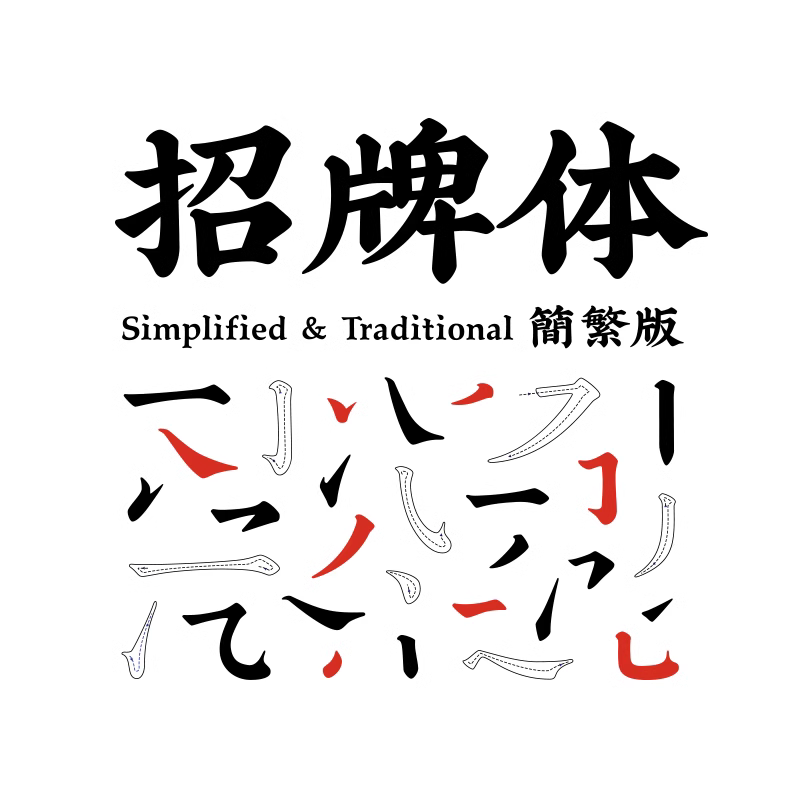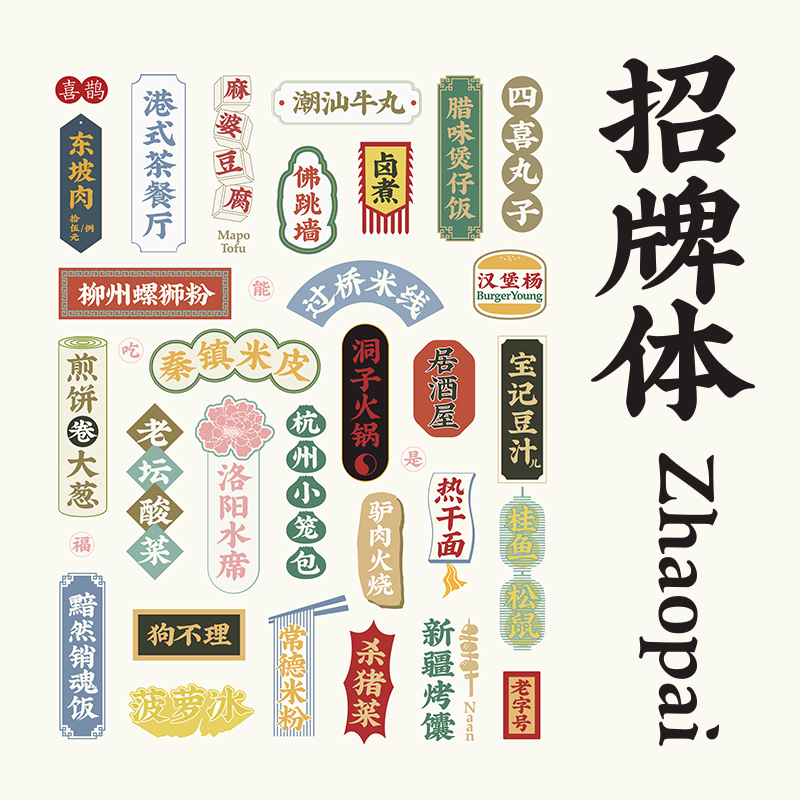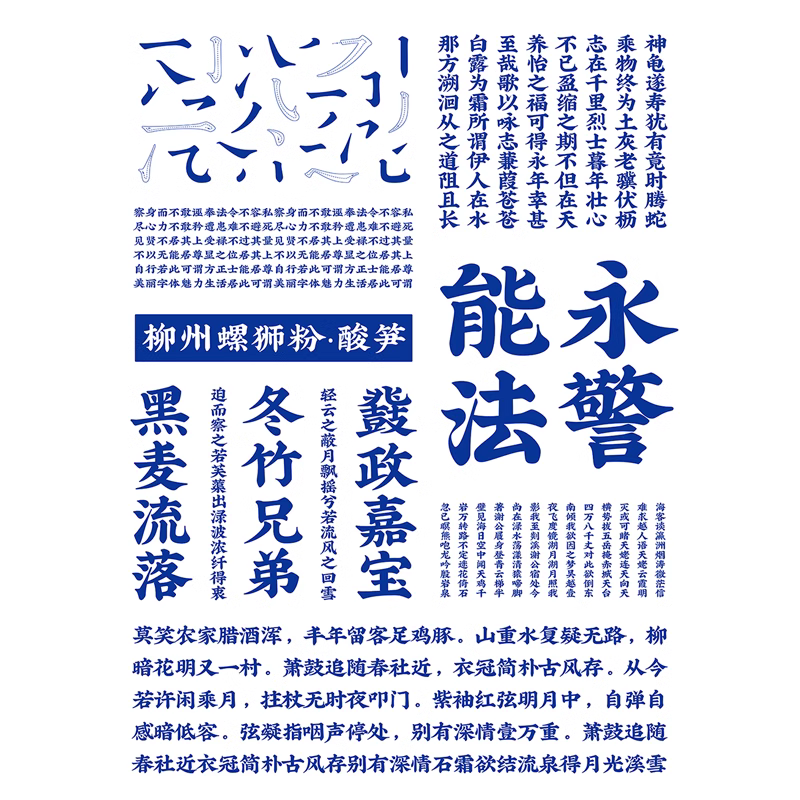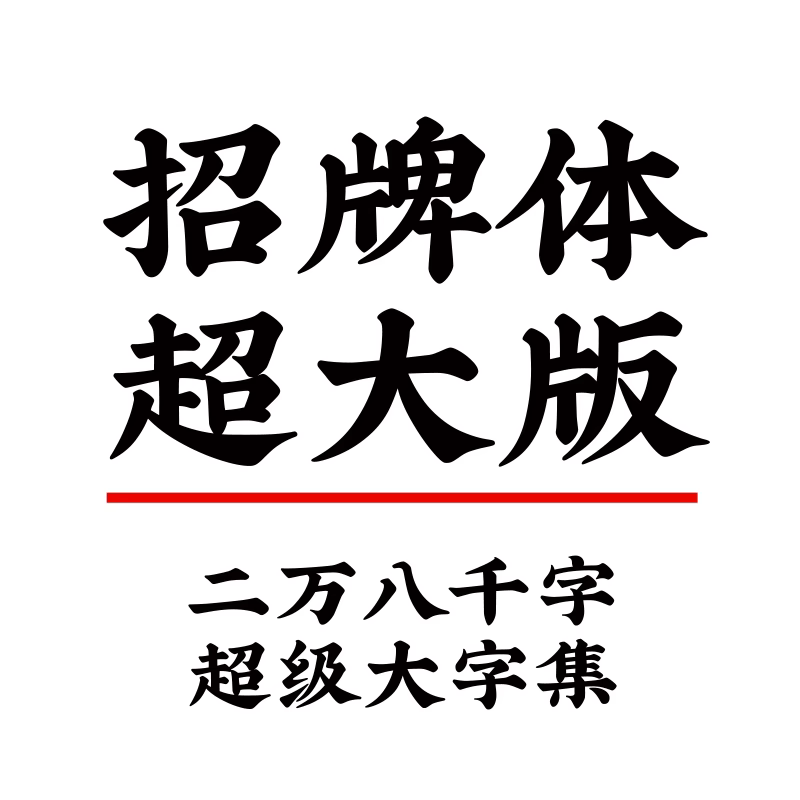
【喜鹊招牌体】字体介绍:
参照嘉靖时期古籍魁本大字本五经古字而创作,设计上追求一种朴实、诚恳、有亲近感有气质的书法风格现代字体。
适用风格:适用于中式味道偏复古的标志标题等文字需求,如餐饮、文创品牌、中式食品、影视字幕等。
2017 Granshan非拉丁文字体大赛-Special Mention 奖
第八届方正奖字体设计大赛-入围奖
HiiiTypography2016字体设计大赛-入围奖